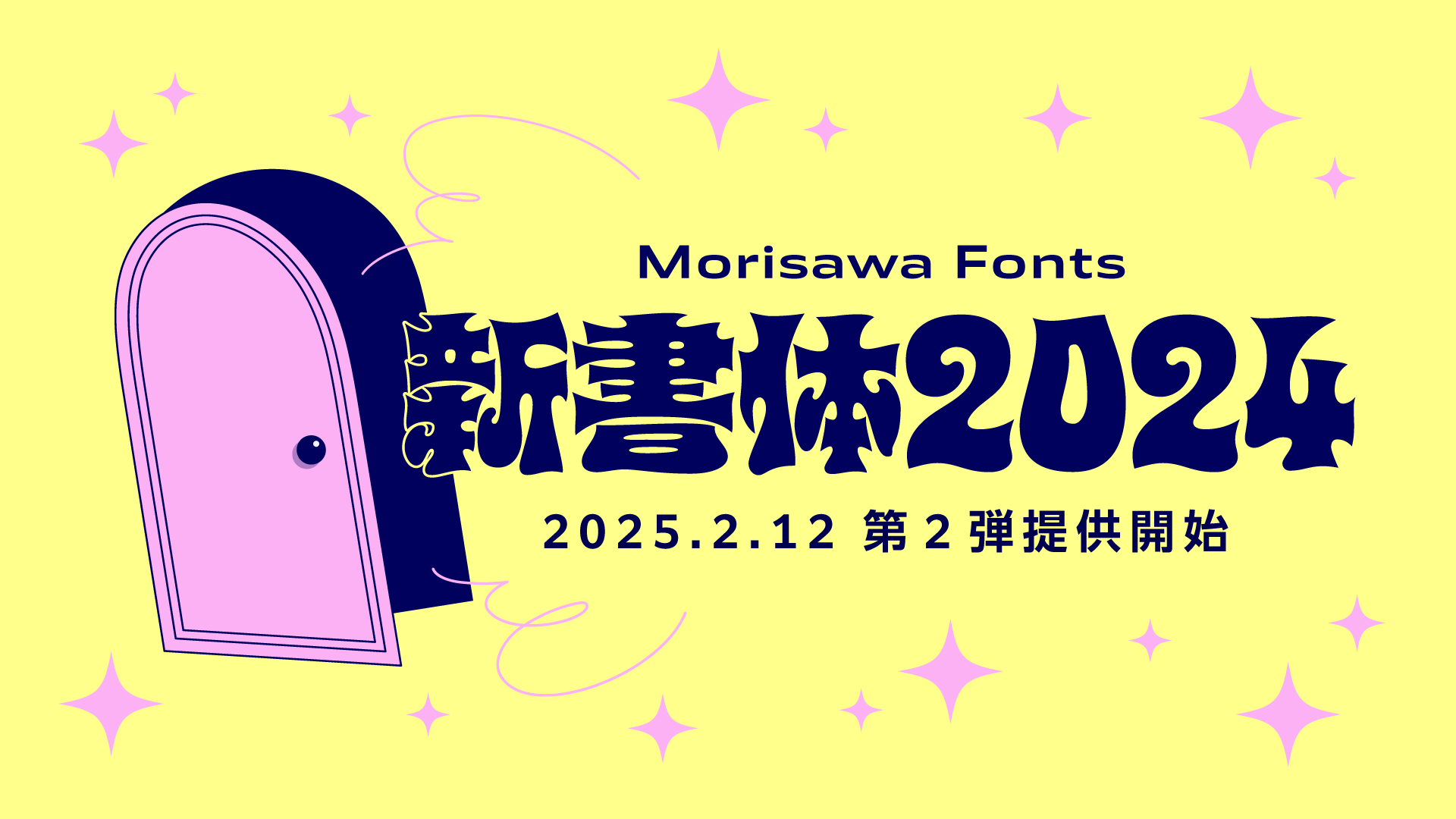
モリサワ初のバリアブルフォントなど新書体の第2弾を2月12日11時よりMorisawa Fontsで提供開始
株式会社モリサワ(以下モリサワ)は、2025年2月12日(水)11時より、Morisawa Fontsアップグレード2025年2月版として2024年度新書体第2弾の提供を開始します。
今回のアップグレードで追加するのは合計37ファミリーです。モリサワ初のバリアブルフォント「DriveFlux」は、シンプルでシンメトリーな骨格と幾何学的なストロークで構成された和文書体として、見出しなど目を引きたいシーンにおすすめです。また、欧文スーパーファミリー「Role」に東南アジアやインドで使用される文字に対応する14の多言語展開ファミリーが、「Clarimo UD」シリーズにハングル書体が加わり、さらに多くの言語で統一感のある表現を叶えます。アメリカに拠点を置く書体ライブラリOccupant Fontsからは、機械的で無骨なスラブセリフ体「Dispatch 2」や見出し利用に適した骨太で重厚感のあるサンセリフ体「Magmatic」などの欧文ラインナップが登場します。ぜひアクティベートしてご利用ください。
DriveFlux |
Clarimo UD KR |
Role Sans Bangla |
Role Sans Devanagari |
Role Sans Gujarati |
Role Sans Gurmukhi |
Role Sans Kannada |
Role Sans Khmer |
Role Sans Lao |
Role Sans Malayalam |
Role Sans MeiteiMayek |
Role Sans Odia |
Role Sans Tamil |
Role Sans Telugu |
Thin / ExtraLight / Regular / Medium / Bold / ExtraBold / Heavy / Black |
|
Role Sans Thai |
Thin / Thin Italic / ExtraLight / ExtraLight Italic / Light / Light Italic / Regular / Italic / Medium / Medium Italic / Bold / Bold Italic / ExtraBold / ExtraBold Italic / Heavy / Heavy Italic / Black / Black Italic |
|
Role Sans Urdu |
Thin / ExtraLight / Regular / Medium / Bold / ExtraBold / Heavy / Black |
〈Occupant Fonts〉
|
ファミリー名 |
ウエイト |
|
Zócalo Banner |
Regular / Italic / SemiBold / SemiBold Italic / Bold / Bold Italic / Black / Black Italic |
|
Prensa |
Light / Light Italic / Book / Book Italic / Regular / Italic / SemiBold / SemiBold Italic / Bold / Bold Italic / Black / Black Italic |
|
Quiosco Display |
Regular / Italic / SemiBold / SemiBold Italic / Bold / Bold Italic / Black / Black Italic |
|
Dispatch 2 |
ExtraLight / ExtraLight Italic / Light / Light Italic / Regular / Italic / SemiBold / SemiBold Italic / Bold / Bold Italic |
|
Dispatch 2 Condensed |
ExtraLight / ExtraLight Italic / Light / Light Italic / Regular / Italic / SemiBold / SemiBold Italic / Bold / Bold Italic |
|
Dispatch 2 Compressed |
ExtraLight / ExtraLight Italic / Light / Light Italic / Regular / Italic / SemiBold / SemiBold Italic / Bold / Bold Italic |
|
Dispatch 2 Wide |
ExtraLight / ExtraLight Italic / Light / Light Italic / Regular / Italic / SemiBold / SemiBold Italic / Bold / Bold Italic |
|
Dispatch 2 Extended |
ExtraLight / ExtraLight Italic / Light / Light Italic / Regular / Italic / SemiBold / SemiBold Italic / Bold / Bold Italic |
|
Magmatic |
Thin / ExtraLight / Regular / Bold / Black |
|
Magmatic Condensed |
Thin / ExtraLight / Regular / Bold / Black |
|
Magmatic Compressed |
Thin / ExtraLight / Regular / Bold / Black |
|
Magmatic Wide |
Thin / ExtraLight / Regular / Bold / Black |
|
Magmatic Extended |
Thin / ExtraLight / Regular / Bold / Black |
|
Rapport |
Thin / Thin Italic / ExtraLight / ExtraLight Italic / Light / Light Italic / Regular / Italic / Bold / Bold Italic / Black / Black Italic |
|
Stainless 2 |
ExtraLight / ExtraLight Italic / Light / Light Italic / Regular / Italic / SemiBold / SemiBold Italic / Bold / Bold Italic |
|
Stainless 2 Condensed |
ExtraLight / ExtraLight Italic / Light / Light Italic / Regular / Italic / SemiBold / SemiBold Italic / Bold / Bold Italic |
|
Stainless 2 Compressed |
ExtraLight / ExtraLight Italic / Light / Light Italic / Regular / Italic / SemiBold / SemiBold Italic / Bold / Bold Italic |
|
Stainless 2 Wide |
ExtraLight / ExtraLight Italic / Light / Light Italic / Regular / Italic / SemiBold / SemiBold Italic / Bold / Bold Italic |
|
Stainless 2 Extended |
ExtraLight / ExtraLight Italic / Light / Light Italic / Regular / Italic / SemiBold / SemiBold Italic / Bold / Bold Italic |
|
Gasket |
Thin / Thin Italic / ExtraLight / ExtraLight Italic / Light / Light Italic / Regular / Italic / SemiBold / SemiBold Italic / Bold / Bold Italic |
|
Eggwhite |
Lite / Black |